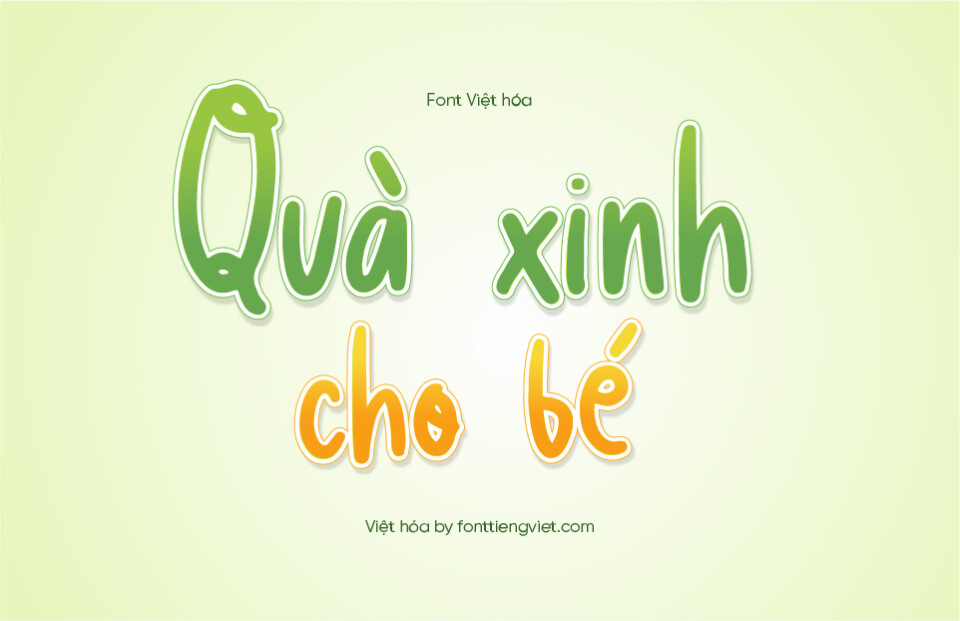
Font Việt hóa 1FTV VIP Wonderful Magic
Font Việt hóa 1FTV VIP Wonderful Magic – Bộ font chữ thần tiên cho thiết kế giáo dục
Giới thiệu về Font Việt hóa 1FTV VIP Wonderful Magic
Trong thế giới thiết kế đồ họa dành cho lứa tuổi học sinh và môi trường học đường, việc lựa chọn một bộ Font Miễn Phí có phong cách trẻ trung và mang tính sáng tạo luôn là ưu tiên hàng đầu. Font Việt hóa 1FTV VIP Wonderful Magic chính là giải pháp hoàn hảo mang đến hơi thở kỳ ảo, giúp các bài giảng và ấn phẩm truyền thông trường học trở nên sinh động hơn bao giờ tự hết. Đây là một bộ font chữ được tinh chỉnh kỹ lưỡng về mặt hiển thị, đảm bảo đầy đủ các dấu tiếng Việt mà không bị lỗi chân chữ hay mất nét, giúp người dùng dễ dàng ứng dụng vào nhiều phần mềm thiết kế khác nhau. Với cảm hứng từ những câu chuyện cổ tích và phép thuật, bộ font này tạo ra một không gian hình ảnh đầy mộng mơ và lôi cuốn người xem ngay từ cái nhìn đầu tiên.
Những đặc điểm nổi bật của Font Việt hóa 1FTV VIP Wonderful Magic
Thiết kế mềm mại và giàu cảm xúc
Đúng như tên gọi của mình, Font Việt hóa 1FTV VIP Wonderful Magic sở hữu những đường nét uốn lượn mềm mại nhưng vẫn giữ được sự rõ ràng cần thiết. Các ký tự được tạo hình với độ dày vừa phải, tạo cảm giác thân thiện và gần gũi. Điều này rất phù hợp cho việc thiết kế bìa sách giáo khoa, các mẫu thời khóa biểu hay bảng tin lớp học. Sự kết hợp giữa yếu tố nghệ thuật và tính ứng dụng cao giúp bộ font này trở thành lựa chọn yêu thích của các thầy cô giáo và các bạn học sinh yêu thích trang trí sổ tay (bullet journal).
Khả năng tương thích và tối ưu hóa tiếng Việt
Điểm cộng lớn nhất của Font Việt hóa 1FTV VIP Wonderful Magic chính là sự chỉn chu trong khâu Việt hóa. Các dấu thanh như dấu huyền, sắc, hỏi, ngã, nặng được đặt ở vị trí hợp lý, cân đối với chữ cái chính, tránh tình trạng bị đè nét hoặc quá xa ký tự. Điều này giúp văn bản khi in ấn hoặc trình chiếu trên slide PowerPoint luôn giữ được sự chuyên nghiệp và dễ đọc nhất cho các em học sinh.
Ứng dụng Font Việt hóa 1FTV VIP Wonderful Magic trong học đường
Trang trí bài giảng điện tử và slide thuyết trình
Việc sử dụng Font Việt hóa 1FTV VIP Wonderful Magic cho các tiêu đề lớn trong bài giảng giúp thu hút sự chú ý của học sinh hiệu quả hơn. Thay vì những bộ font hệ thống khô khan, nét chữ “phép thuật” này sẽ khơi gợi trí tưởng tượng và sự hứng thú trong mỗi tiết học. Bạn có thể sử dụng font cho các trò chơi học tập hoặc các câu hỏi đố vui để tạo điểm nhấn khác biệt.
Thiết kế thiệp mời và băng rôn sự kiện trường học
Vào các dịp lễ hội như Trung thu, Giáng sinh hay ngày Nhà giáo Việt Nam, bộ font này phát huy tối đa sức mạnh của mình. Những tấm thiệp mời hay băng rôn chào mừng được thiết kế với phong cách Wonderful Magic sẽ tạo nên một không khí lễ hội ngập tràn màu sắc và niềm vui.
Kết luận về bộ Font Việt hóa 1FTV VIP Wonderful Magic